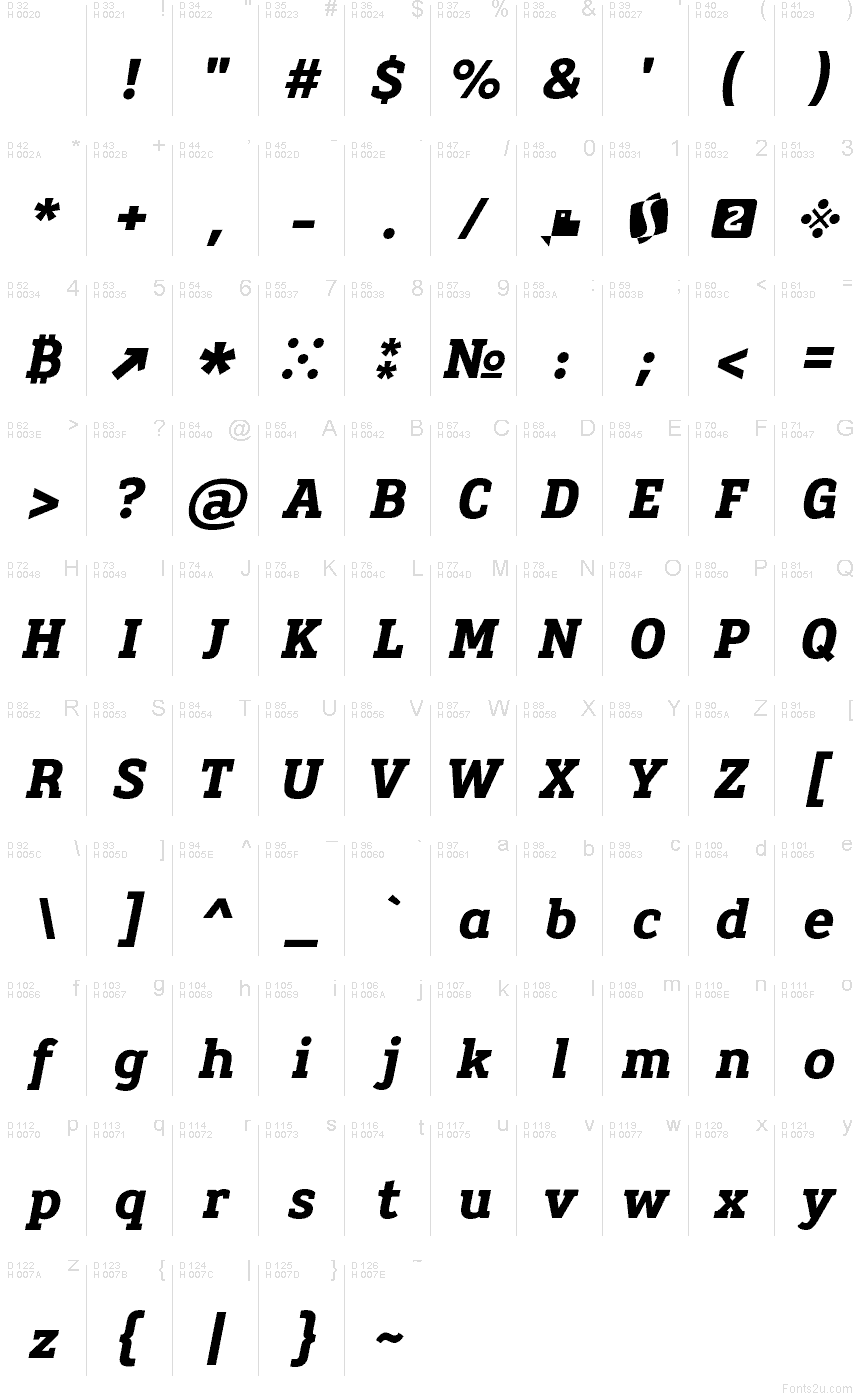
Biotrip Serif Bold Italic
Biotrip Serif Bold Italic, da deFharo, é uma fonte serifada cursiva gratuita com uma silhueta larga, inclinada para a frente e serifas em forma de cunha que conferem às letras um efeito esculpido e cartazista. As curvas arredondadas e as junções espessas impedem que esse movimento pareça cortante ou frágil, resultando num design simultaneamente denso e fluido.
Essa combinação dá aos títulos curtos um papel de destaque em capas de livros, publicações, cartazes de filmes, embalagens e citações dramáticas. Também é ideal para branding, onde a inclinação e a força das serifas podem conferir personalidade a um logotipo sem torná-lo demasiado mecânico ou formal.
Biotrip Serif Italic is a friendly typeface family that is, above all, a journey. A journey (Trip) from the purity of geometry to the warmth of the organic (Bio).
Biotrip Serif Italic comprises 14 methodically designed fonts, distributed across 2 styles (Regular and a genuine, flowing Italic) and 7 weights, ranging from the ethereal elegance of Light to the powerful impact of Black.